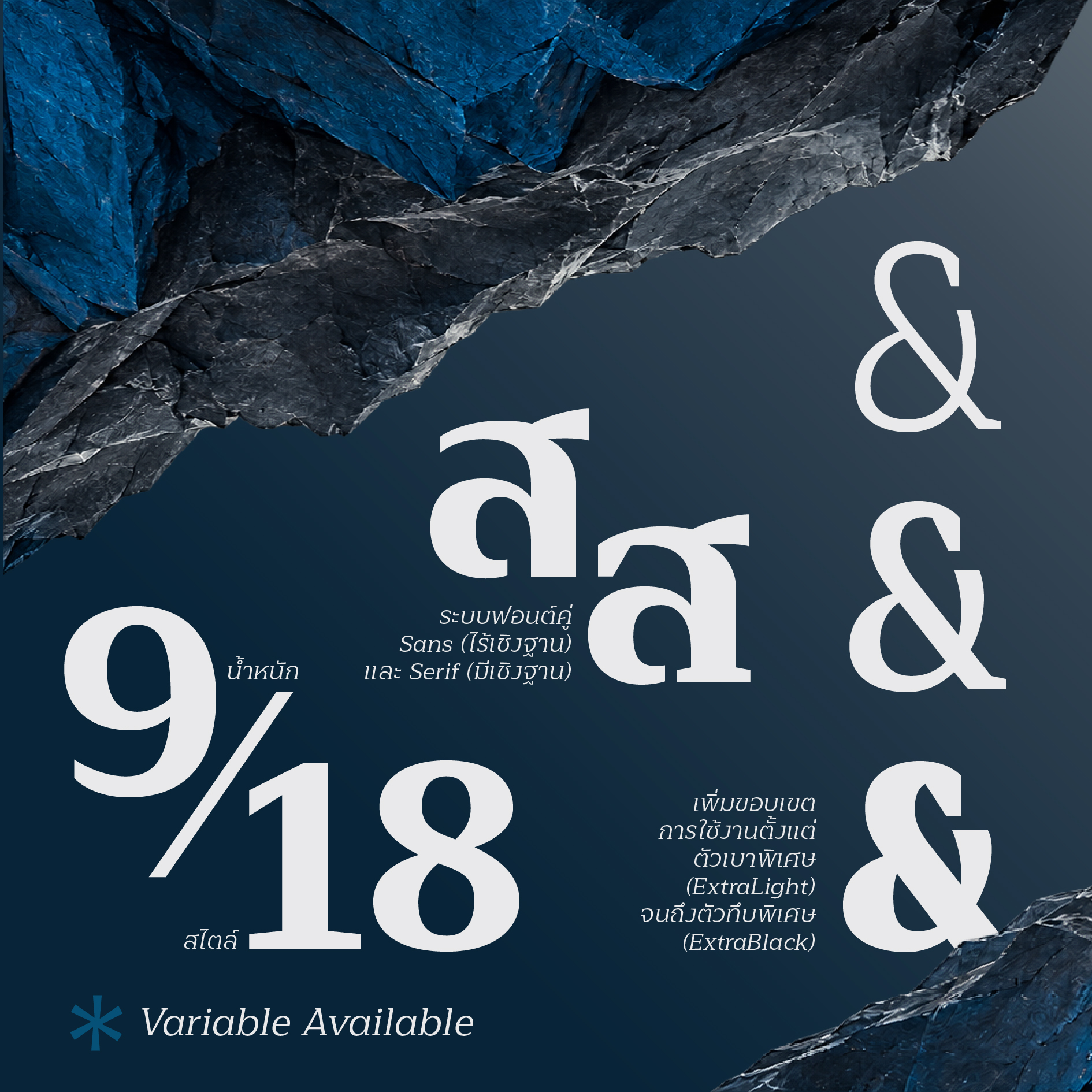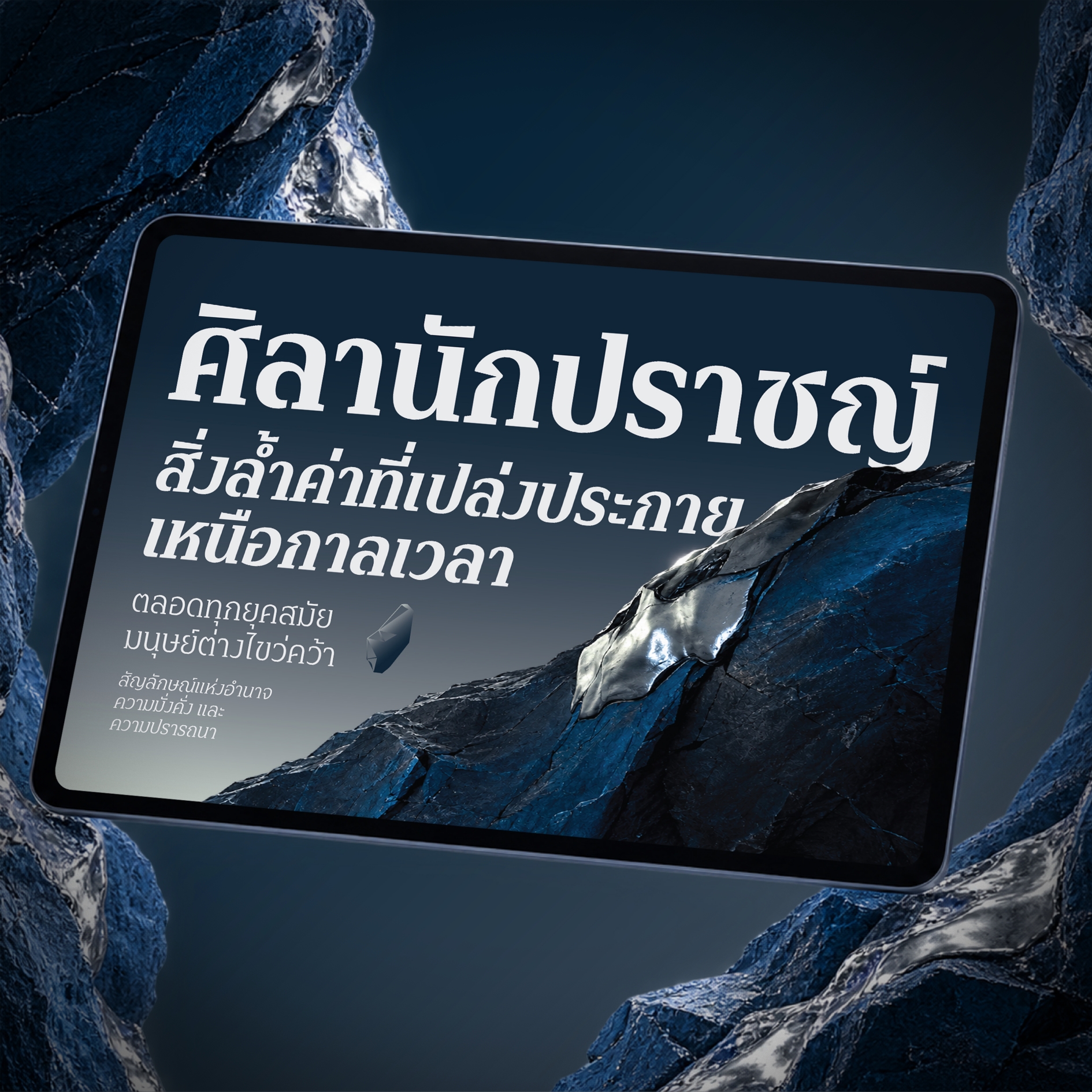
เอฟซี มีสกุล เซอริฟ (FC Mee Sakul Serif)
ฟอนต์เอฟซี มีสกุล เซอริฟ (FC Mee Sakul Serif)
Classic Luxury Typeface
ความหรูหราแบบคลาสสิก แสดงออกอย่างมีชั้นเชิง
ออกแบบภายใต้แนวคิดระบบฟอนต์คู่ระหว่าง Sans ไร้เชิงฐานของฟอนต์เอฟซี มีสกุล และ Serif มีเชิงฐานของฟอนต์เอฟซี มีสกุล เซอริฟ เกิดเป็นฟอนต์สองชุดที่มีโครงสร้างเดียวกันแต่ต่างอารมณ์
เชิงฐานสร้างชั้นเชิง มีรากฐาน น่าเชื่อถือ ให้ความคลาสสิกแบบดั้งเดิม โดยการออกแบบไม่ได้เป็นการเพิ่มเชิงฐานเข้าไปตรงๆ แต่ยังมีการจัดการพื้นที่ภายในและพื้นที่ภายนอกตัวอักษรใหม่ เพื่อให้เชิงฐานที่เพิ่มไปเป็นส่วนเติมเต็ม ไม่เป็นส่วนเกิน
มาพร้อม 9 ระดับความกว้างและตัวเอนรวม 18 สไตล์ มี Variable Font แยกจากชุดปกติ
Font Information: เอฟซี มีสกุล เซอริฟ (FC Mee Sakul Serif)